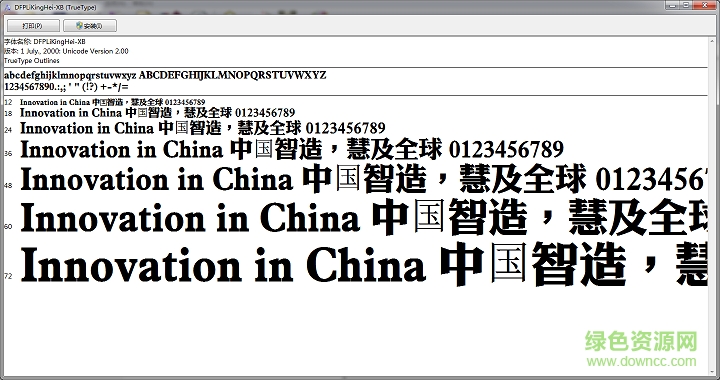
華康儷金黑繁體是一款繁體字體,它的文字效果是加黑加粗并且非常端正,可用于logo設(shè)計(jì)或者其他顯目的標(biāo)題文字,歡迎來綠色資源網(wǎng)下載使用!
華康科技成立于1987年,以尖端的造字技術(shù)起家,為中文世界提供了高效率的傳播橋梁。
十幾年來,華康科技始終秉持“專業(yè)、創(chuàng)新、藝術(shù)”的信念,跟著時(shí)代脈動不斷成長。
作為亞洲文字著名制造商和供應(yīng)商,華康科技本著“字里圖間,溝通世界”的理念,開發(fā)高品位、自創(chuàng)華康字型(DynaFont)品牌的電腦和印刷用字,在亞洲字庫產(chǎn)品市場占有相當(dāng)份額,在字型技術(shù)上的領(lǐng)先地位。